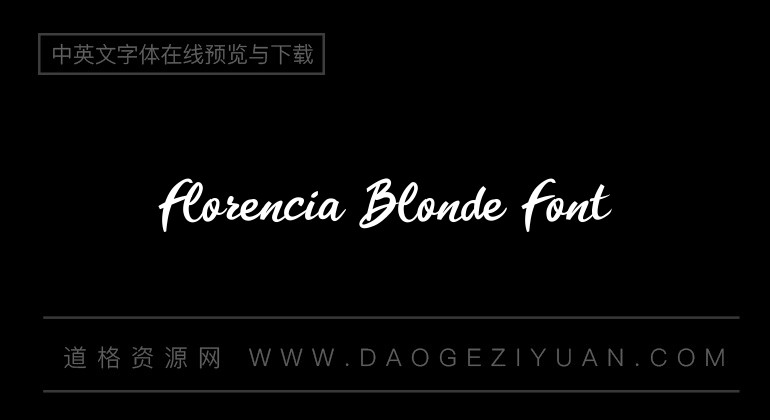
Florencia Blonde Font
Florencia Blonde Font是一种手写风格的字体,适用于各种设计项目,如海报、标志、包装、书籍封面等等。这个字体具有轻快、优美的特点,字母之间的间距也比较适中,易于阅读。Florencia Blonde Font包含大写字母、小写字母、数字和标点符号,字体文件格式包括TTF、OTF、WOFF等多种格式,方便在不同的平台上使用。总的来说,Florencia Blonde Font是一个非常实用、美观的字体,可以为你的设计项目增添一份独特的魅力。
Florencia Blonde Font是一款非常不错的手写艺术字体,具有很好的视觉感,适合于文化类的宣传设计、商业类品牌的广告和产品包装设计以及个性化文字排版等较多场景。